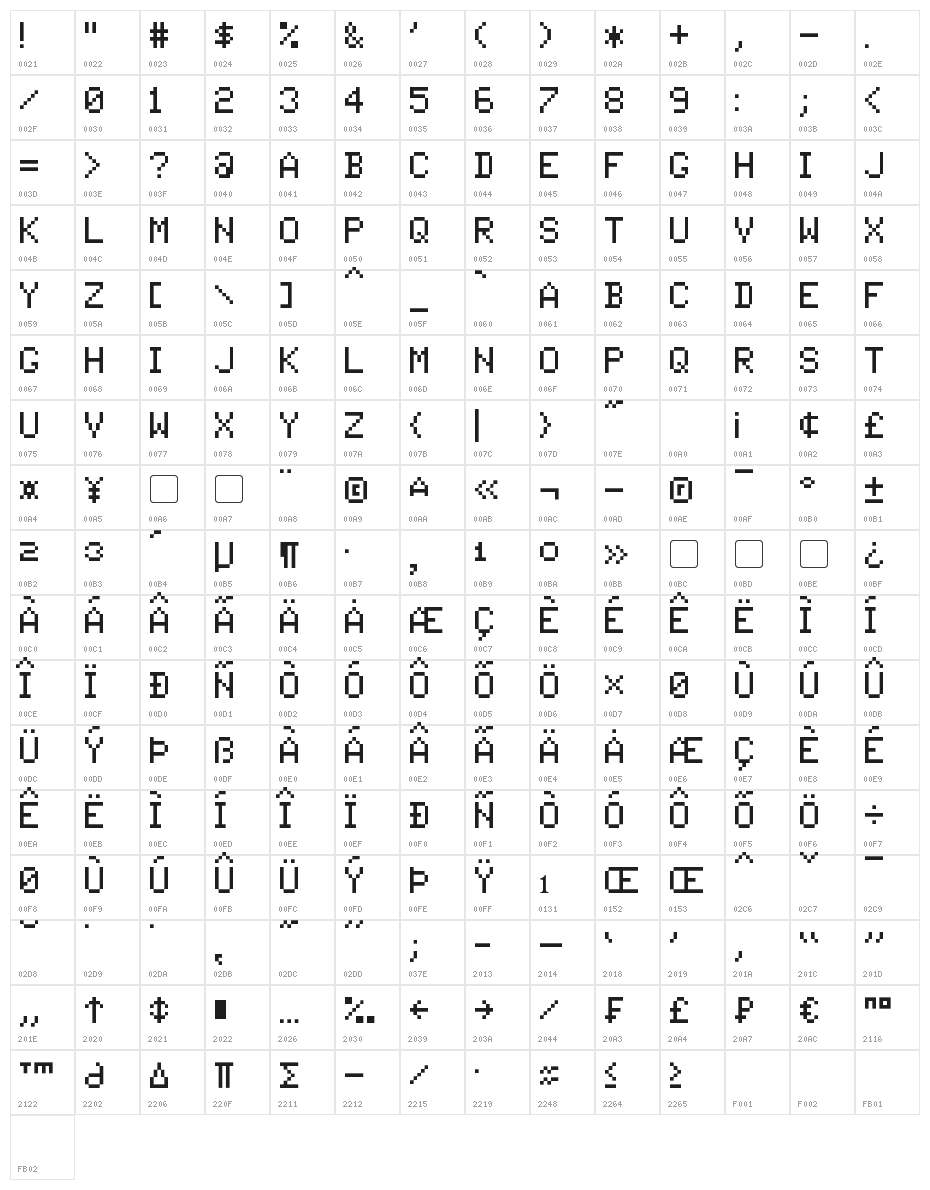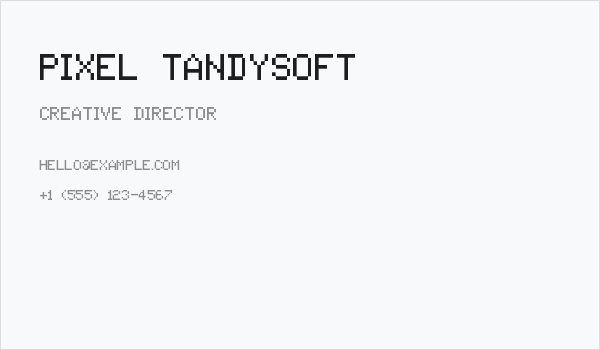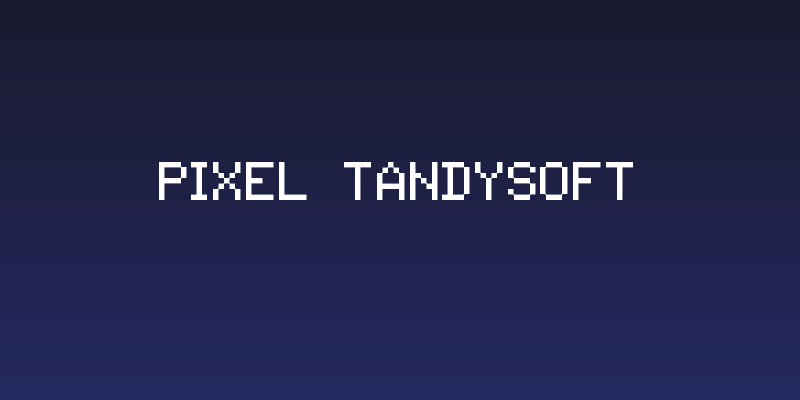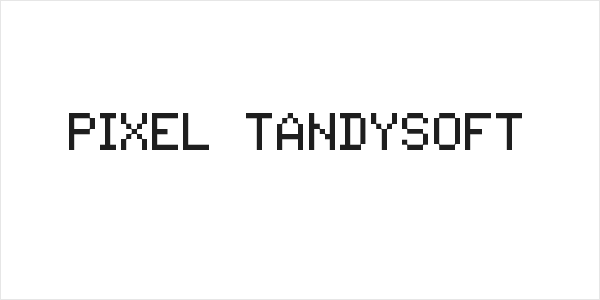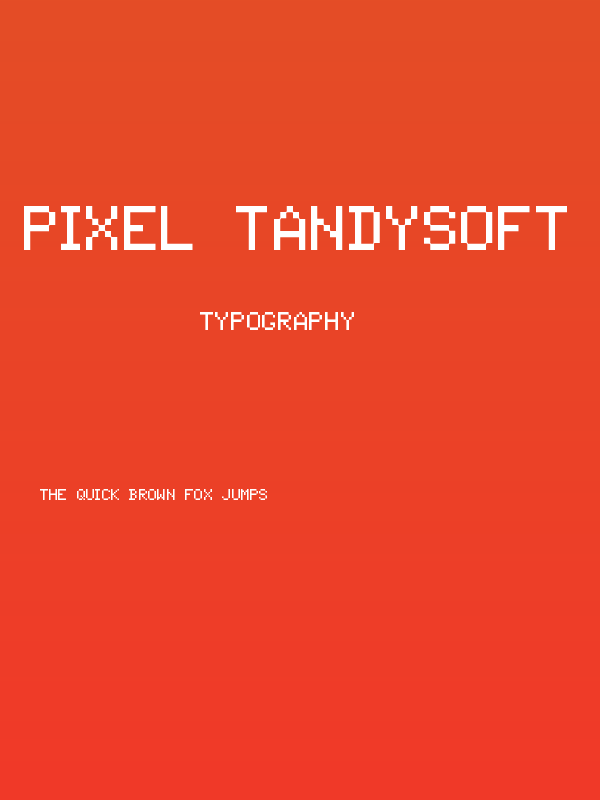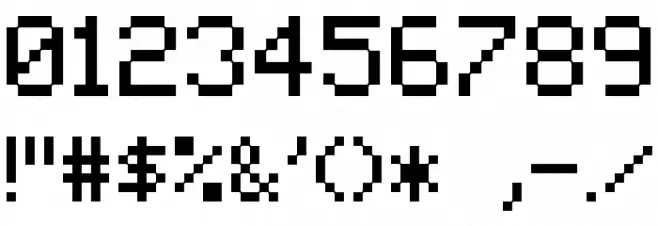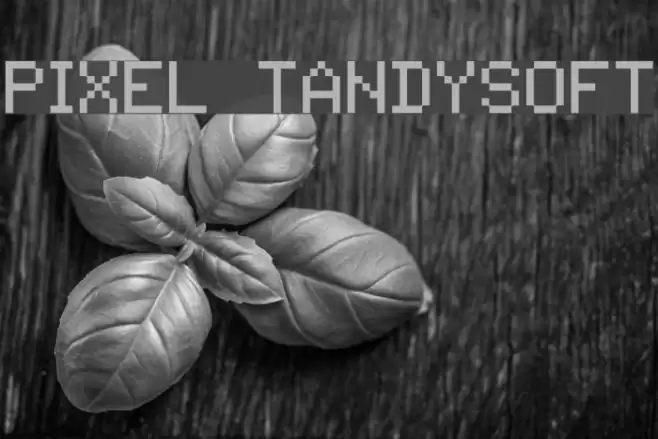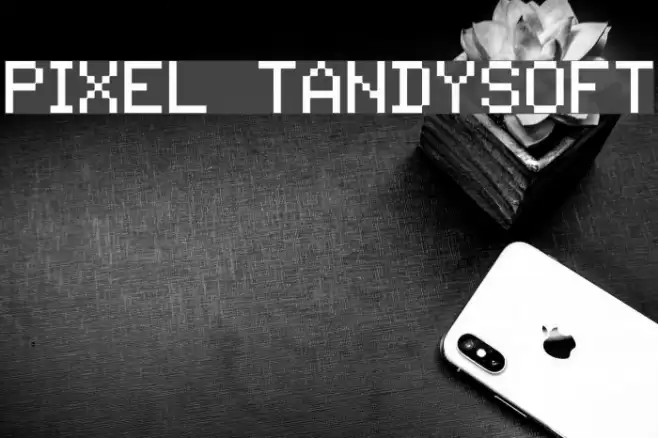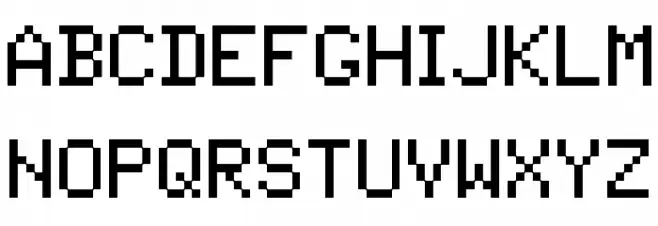
Pixel Tandysoft Font
| Gesamtstil | Vintage |
| Anwendungsfall | Digital displays, Coding, Retro-themed projects |
| Vorgeschlagene Projekte | Ideal for retro video games, digital art, coding environments, and nostalgic branding. |